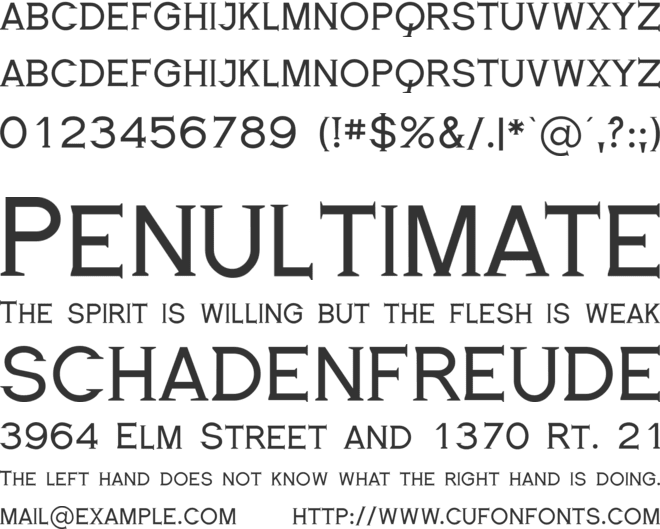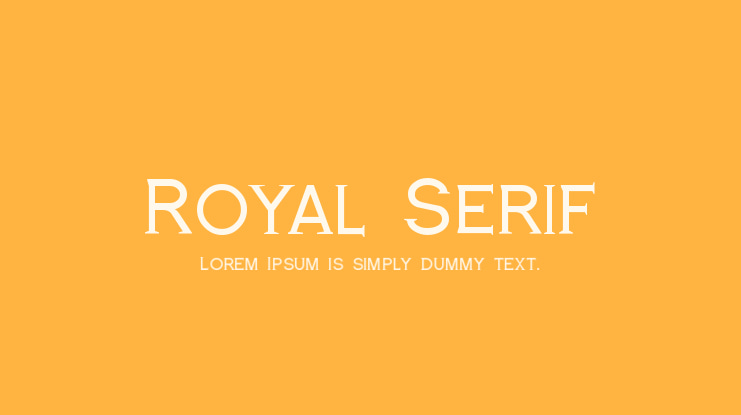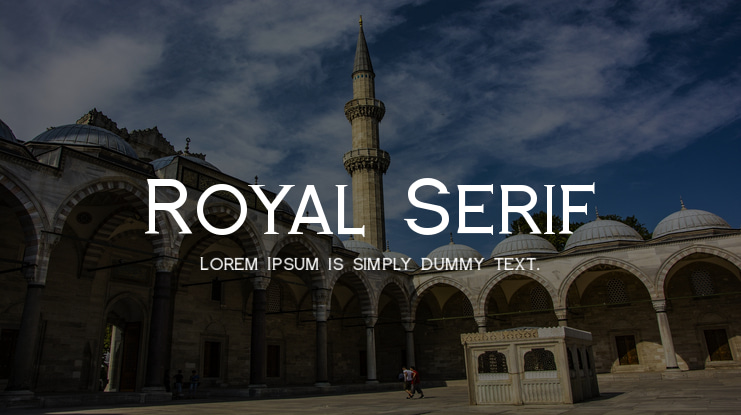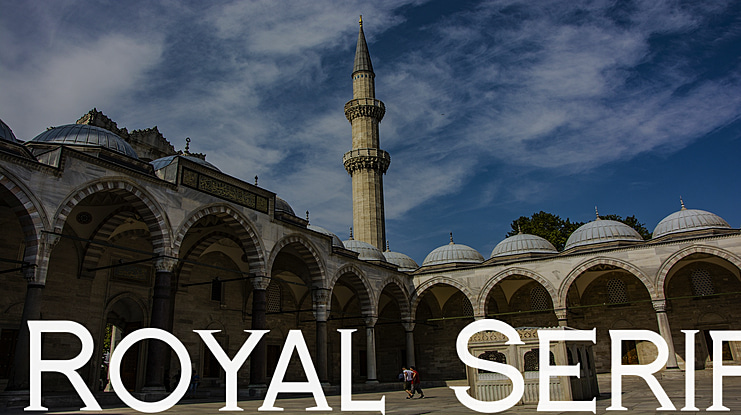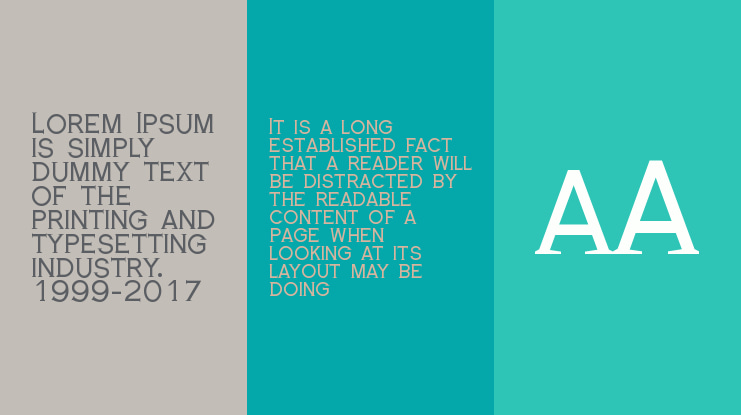
Royal Serif Font
Tipografia Vittoria
Serif Royal è un font serif con maiuscolo/maiuscoletto dalle linee molto classiche, le grazie ricordano molto il cosiddetto "stile romano". Questo font è adatto a grafiche di stampo classico quali biglietti da visita e carta da lettere per liberi professionisti od aziende di tipo tradizionale.